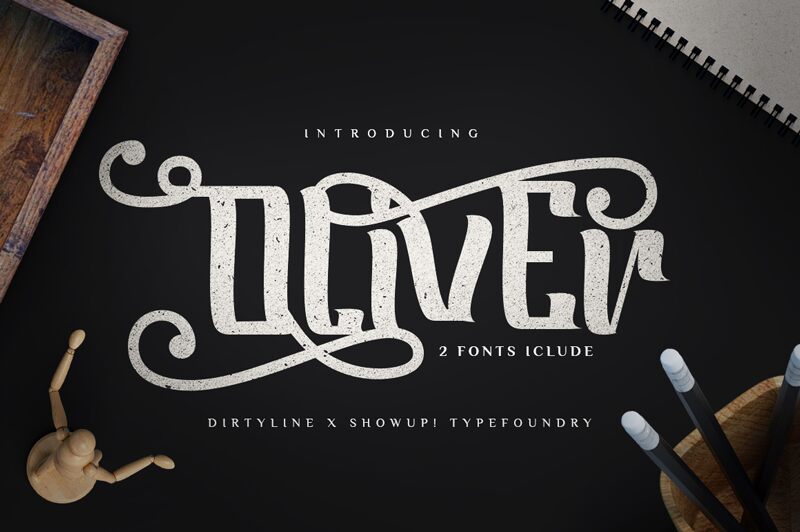
Oliver von der ShowUp! Typefoundry ist eine kostenlose Display-Schrift mit hohen, schmalen Lettern, abgerundeten Verbindungen und scharfen, blockartigen Serifen, die ihr einen kantigen, redaktionellen Look verleihen. Die Formen kombinieren weiche Kurven mit abrupten, vertikalen Schnitten, wodurch die gesamte Schrift eher maßgeschneidert als rein dekorativ wirkt.
Oliver eignet sich hervorragend für Logodesigns, Plakatüberschriften, Verpackungen, redaktionelle Headlines und Albumcover, da die starke Silhouette einen unverwechselbaren Charakter transportiert, ohne dass es zusätzlicher Dekoration bedarf. Diese kostenlose Schrift ist zudem ideal für Modelabels, Restaurant-Branding und kurzen Anzeigentext, bei denen es mehr auf eine kompakte, stilisierte Form ankommt als auf reine Funktionalität.